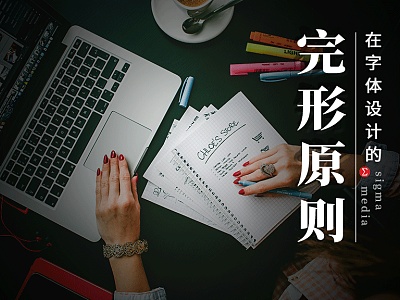
怎样让字在视觉上无可挑剔?字体设计中完形法则的应用
平面设计就是将各种元素在二维的空间内进行排列组合,以达到审美的趣味,字体设计也属于此但又不止于此,横竖撇捺、一笔一划既要满足视觉审美还要表达丰富含义。
那怎样让设计的字在视觉上和内涵上都无可挑剔?不要急,完形法则(Law of Organization)在字体设计中的应用你该知道了。
一、完形法则只知其名不知其意?
完形法则是以完形心理学为依据的,认为“整体不等于个体的总合”,也就是说我们看到一个字时,并不是先看到横竖撇捺的笔画然后认为这是一个很多笔画堆砌成的字,而是直接感知到这是一个整体的字。
完形法则应用领域很广,我么这里说的其实仅指完形心理学的视觉法则。
因为这一理论认为整体不是部分的简单总和或相加,不是由部分决定的,而是各个部分由这个整体的内部结构和性质所决定的,这也就意味着人们在知觉事物时总会按照一定的准则,那这个准则就是我们这里说的完形法则。
同样的,无论是平面设计还是字体设计,别人看到作品,视觉上并不会完全客观的产生感知,而是会有一些特别的倾向性,这些倾向性就遵循完形法则的规律。
二、完形法则都有哪些规律?
具体来说,完形法则有图底法则、闭合法则、相似法则、接近法则和连续法则,我我们就从这五个方面研究下完形法则在字体设计中的应用。
1.图 底 法 则
这个你肯定不陌生,就是图和底随时可以转换,平面设计中常称为“互为图底”、“图底反转”等,经典的鲁宾杯又要出镜了,日本平面设计大师福田繁雄就因正负图形设计广为人知。
通常情况下面积小的或亮度高的我们会认为是图,而面积大的、亮度低的被认为是底,但完形原则告诉我们,人类并不能全部接受感知对象带来的刺激,总是有选择的感知其中的一部分,所以,就会有图和底互换的现象。
字体设计中也会有这种现象,通常情况下我们感知到的字体本身就是图,那字怀和字周围的空白区域就是底。但如果设计时有意处理笔画的造型和笔画间的构造,就能产生正负形的奇妙转换。
尤其所设计的字是具象含义的字时,比如某种动物、符号等,就能形意结合,表现视觉效果的同时兼顾内涵,可谓形神兼备。
2.闭 合 法 则
看到几个马赛克,你能脑补出30分的动作戏,闭合法则就是指这种强大的脑补能力。
我们在观察事物时,总是倾向将多个独立元素视为一个封闭的图案,就比如有些图形断开了依然不影响识别:
间断的空白部分我们会自动脑补起来,视为连续的图形。小梦曾经分享过字体设计的断舍离思路,汉字笔画断开或舍去我们还能识别出来,正是因为这一法则。
所以说,字体设计中,通过把封闭笔画有意断开、笔画连接处或交叉处断开亦或是根据造型需要舍去个别笔画来设计,既能打破常规视觉产生新奇感,又不会影响到识别。
3.相 似 法 则
古人曰,物以类聚人以群分,诚不欺也,就是应用在视觉领域也是分毫不差!我们感知事物时,就倾向于把相似的事物看成一是体的。
是不是眼睛自动把这些图形归类了?当我们看到的元素在形状、颜色、面积甚至质感等等方面看起来类似或相同时,它们会被不自觉的划为同一个类别。
也就是说,字体设计时几个字的搭配一定要保持笔体的相同和造型手法的类似,否则在视觉上很难感觉是一体的。
4.接 近 法 则
两个人走的比较近,我们就会觉得这两人关系比较好,是同类。视觉上也也是如此,当几个元素被放在相对靠近的位置,即便相似性不大,它们依然会被感知为是同类。
可见,完形原理的接近法则要比相似法则更加能影响到我们的感知,这就是说设计师在设计字体时,一定要注意笔画和字体的位置,恰当处理留白区域!
小到一个字的零散笔画不脱离主体,大到几个字的排版不脱节,只有这样处理好笔画和字体的空间位置关系,才能让设计出来的字体成为一个视觉化的整体。
5.连 续 法 则
不恰当的说,如果你和一个人牵手了,那你两就不再是两只单身狗,也不是两只牵手的单身狗,而是恋人或成为一对。
在视觉上,当两个或两个以上的物体相交时,我们的感知也会把他们认为是一个整体对象,而不是几个物体堆砌在那。
汉字是由横竖撇捺折等笔画组成的,相连、相接、相交的情况躲也躲不过,每一个笔画一旦放到字中,就不再是单纯的横竖撇捺或折,而是汉字的一部分,所以要在整体性的原则下设计个别笔画。
字体设计中有一种常用手法——字体组合,就是几个汉字通过一个共同的笔画或是根据笔画的相似性进行连体,这就是连续法则发挥的作用。
但要注意,一定不要强行笔画连体,因为连续性太强就意味着整体性增强,那么几个字就成为更强的整体势必会影响到各个字的识别!
这么看来,完形原则的五大法则其实就是处理整体和部分之间的关系,让整体视觉呈现完美的效果,而在字体设计中,也就是处理好字体和笔画间的关系,让整体的字体设计呈现出最好的视觉效果。
也就是说,完形原则不仅可以用来指导设计师设计字体,还能用来衡量你设计出来的字是不是达到视觉审美的需求了,所以,完形法则学起来吧,懂这五大特性让你的字完美呈现!